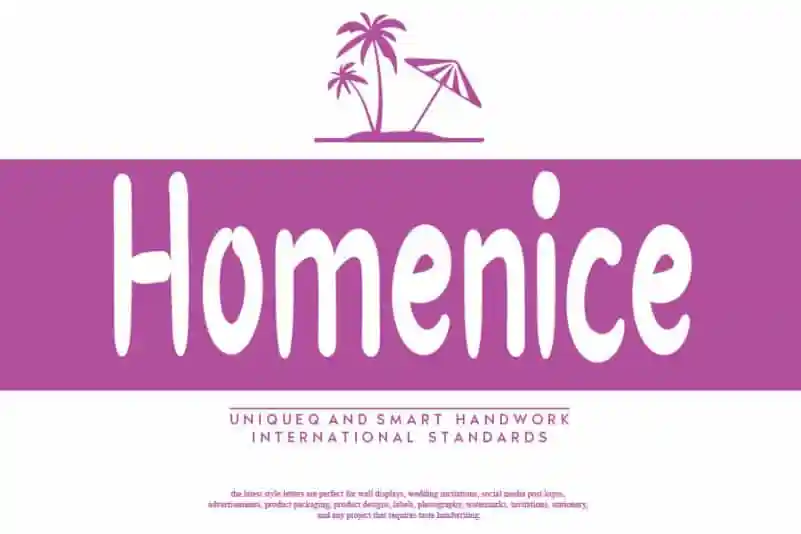
Homenice Script Font – Download Grátis
Homenice Script é uma elegante e amigável fonte escrita à mão que traz um toque suave e natural às suas criações digitais. Suas linhas fluidas e seu estilo único formam uma base ideal para um vasto leque de projetos, desde design gráfico até identidade visual. Com sua aparência tão autêntica quanto única, a Homenice Script Font oferece aos designers o poder de moldar qualquer conceito em realidade visível. Seu principal atributo é a capacidade de adaptar-se às mais variadas necessidades dos projetos, sem limitações — exceto pela imaginação do designer que usa. Para quem busca uma fonte escrita à mão com um toque especial, Homenice Script se destaca como um recurso valioso. Suas linhas elegantes e seu estilo natural tornam esta fonte a escolha perfeita para qualquer projeto que deseje destacar-se no mercado visual contemporâneo. Com o designer na ponta dos lábios, há apenas limites ao que pode ser criado com Homenice Script Font.